요 폰트 무엇인지 꼭 알고싶어요ㅠㅠ
이 폰트 어떤건지 아시는 분 계실까요?
되게 많이 본 것 같은데..
폰트찾기로 돌려보면 ‘산돌 그레타 산스’가 가장 먼저 나오던데
특정 글자에서 모양이 다른걸 보면 다른 폰트인 것 같아요ㅠㅠ
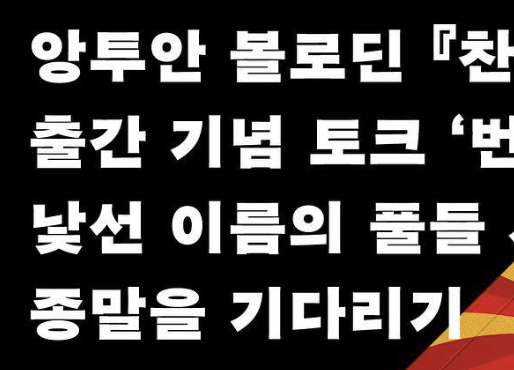
지백 400g 같네요. https://www.tumblbug.com/jibaek?ref=%EA%B2%80%EC%83%89%2F%ED%82%A4%EC%9B%8C%EB%93%9C